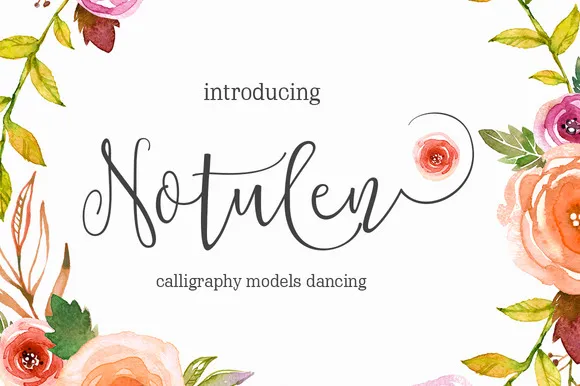
A Notulen é uma fonte tipográfica de escrita artesanal desenvolvida por Hamilton. Esse estilo de escrita única e encantadora se destaca entre as muitas opções disponíveis atualmente. Diferente dos modelos tradicionais de tipografia, a Notulen oferece um toque contemporâneo ao mesmo tempo em que mantém os elementos característicos da arte da escrita artesanal. Ideal para quem busca uma fonte que traz modernidade à sua composição visual, enquanto preserva o encanto do papel e tinta na página. Não é apenas uma opção de fonte; ela se transforma em um verdadeiro acréscimo ao seu design, enriquecendo-o com a personalidade única desta obra de arte tipográfica.